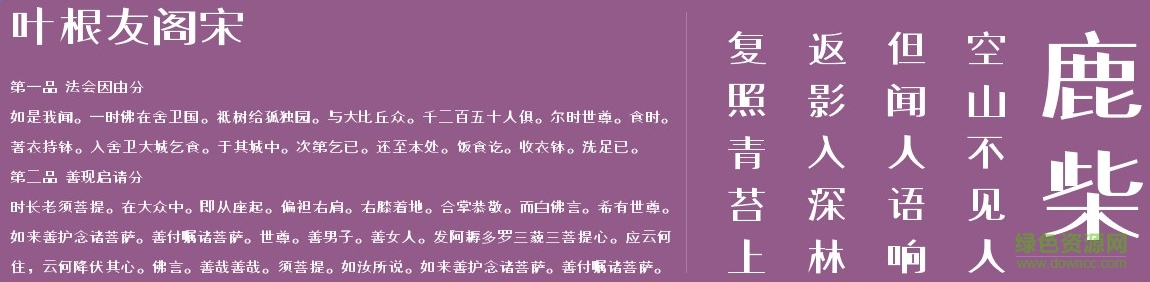
葉根友閣宋字體
葉根友閣宋字體是一款由知名書法家葉根友創(chuàng)造的字體,適用于藝術(shù)設(shè)計(jì)、美工、字體排版等方面,有需要的朋友們不要錯(cuò)過了。小編為大家提供免費(fèi)下載地址。歡迎大家來綠色資源網(wǎng)踴躍下載哦!
官方介紹
葉根友閣宋字體,現(xiàn)代快節(jié)奏的工作中,我們似乎總在追求自由輕松的感覺,這款字體設(shè)計(jì)的設(shè)計(jì)理念就是這樣,非常的扁平化的視覺效果,在字面中讓我們一起來感受。橫豎的粗細(xì)對(duì)比,足以讓視覺沖擊力極強(qiáng)有力。
葉根友閣宋字體
小編點(diǎn)評(píng)
葉根友閣宋字體,用途廣泛,是葉根友先生的印刷字體,字體以宋體字為原型加以打磨變化,適用于文字排版等方面。各位字體收藏者可以來看看。